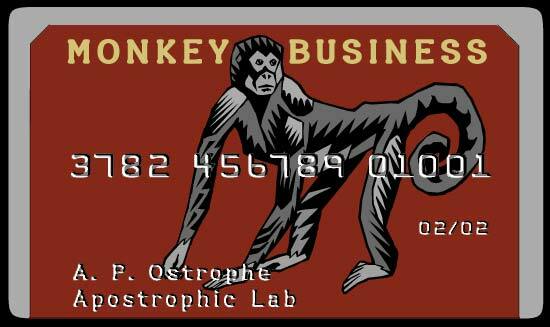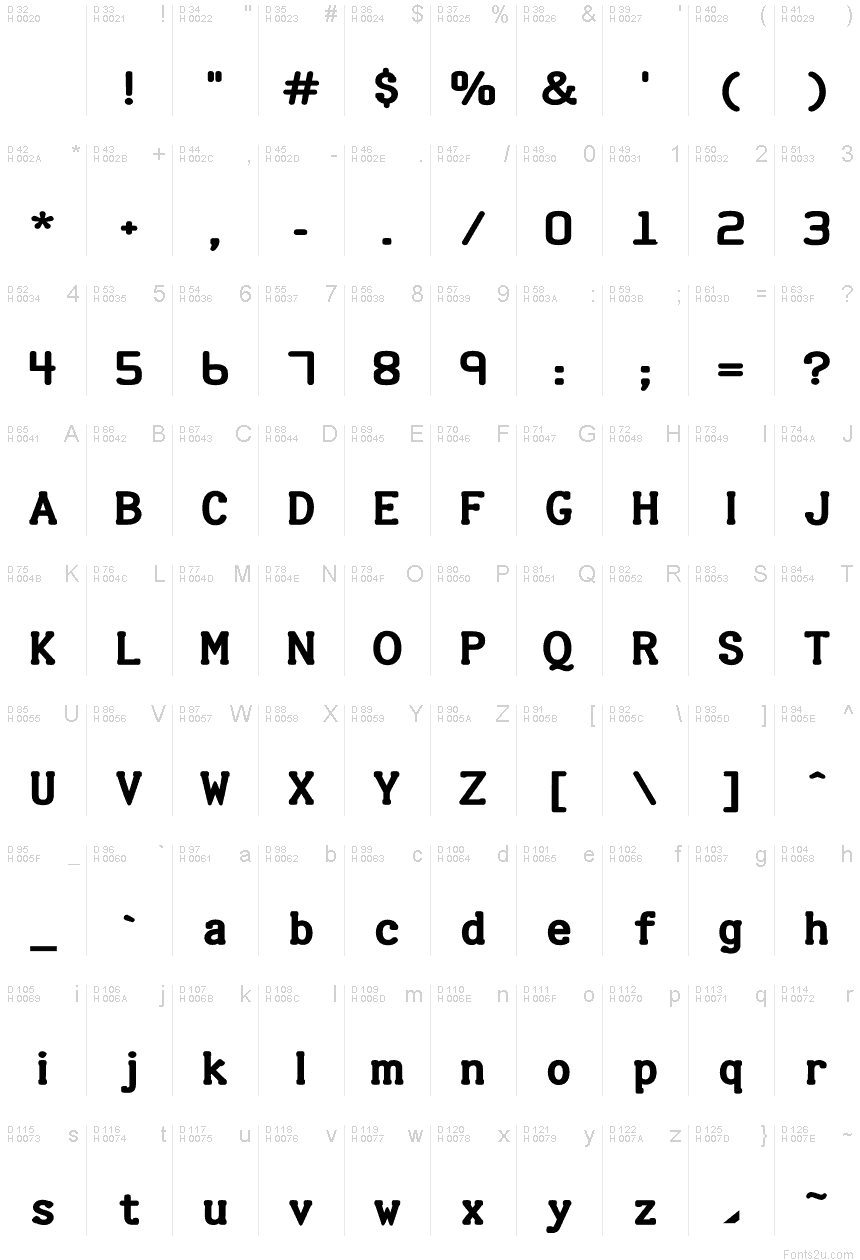
Font Halter od Apostrophic Labs to darmowy, masywny krój szeryfowy, który zamienia dużą wagę w coś ciepłego i przystępnego. Grube, blokowe kształty i miękko zaokrąglone rogi przypominają odcisk pieczątki, nadając tekstowi solidny, namacalny charakter, bez wrażenia surowości czy krzykliwości. Litery są ułożone blisko siebie, tworząc wyraziste, ciemne linie tekstu, które przyciągają uwagę, zachowując przy tym doskonałą czytelność.
Halter sprawia, że nagłówki i krótkie hasła wyglądają jak na solidnym szyldzie – pewnie, przyjaźnie i są łatwe do zauważenia z daleka. Ten darmowy font świetnie sprawdza się w logotypach, plakatach, na opakowaniach, w dziecięcych tytułach, ulotkach, przypinkach i grafikach do mediów społecznościowych, które wymagają mocnego i prostego przekazu. Połącz Halter z czystym, lekkim krojem bezszeryfowym w tekście głównym, a sam Halter wykorzystaj do dużych, wyrazistych nagłówków.
Halter — Prezentacja czcionki